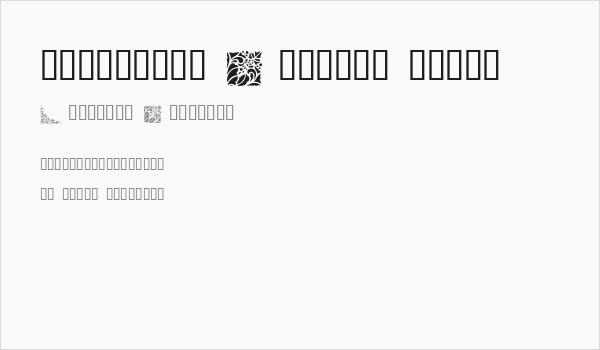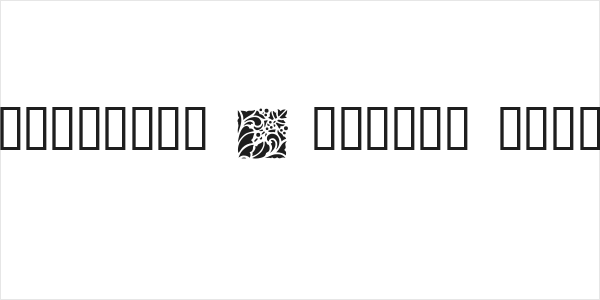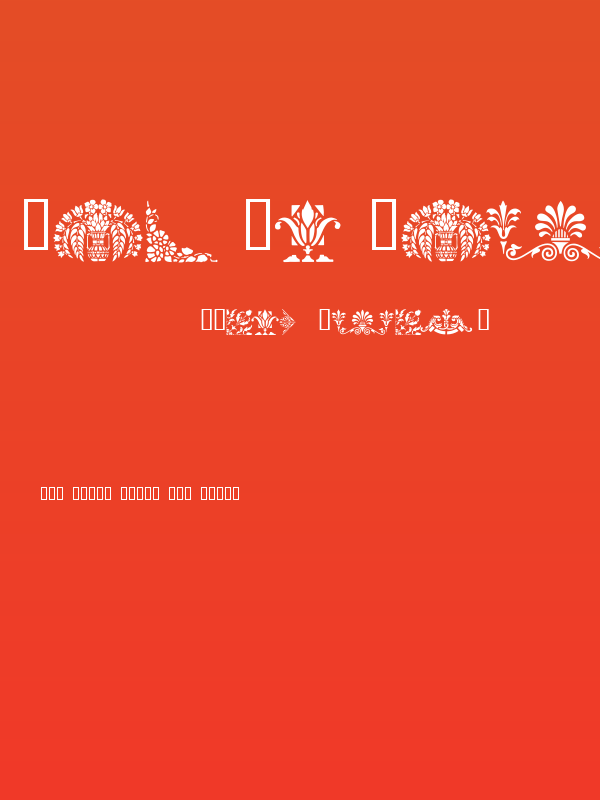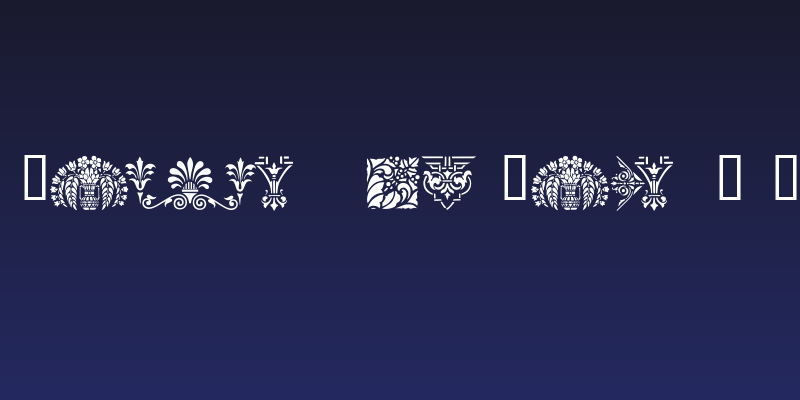
Victorian Designs Three Font
| Caso de uso | Decorative elements, Borders, Invitations |
| Projetos propostos | Ideal for use in vintage-themed invitations, decorative borders, wallpaper designs, and packaging for luxury goods. |